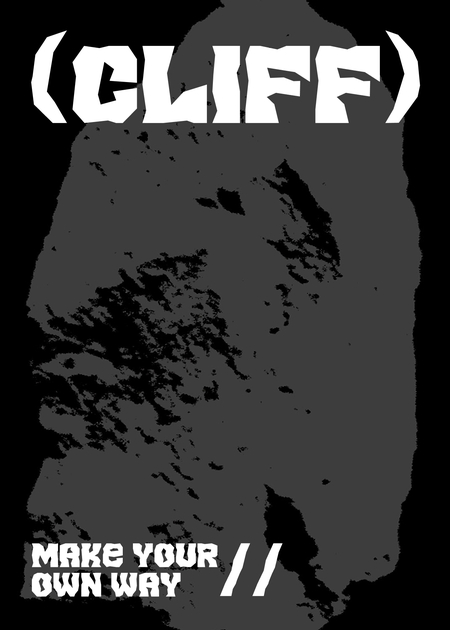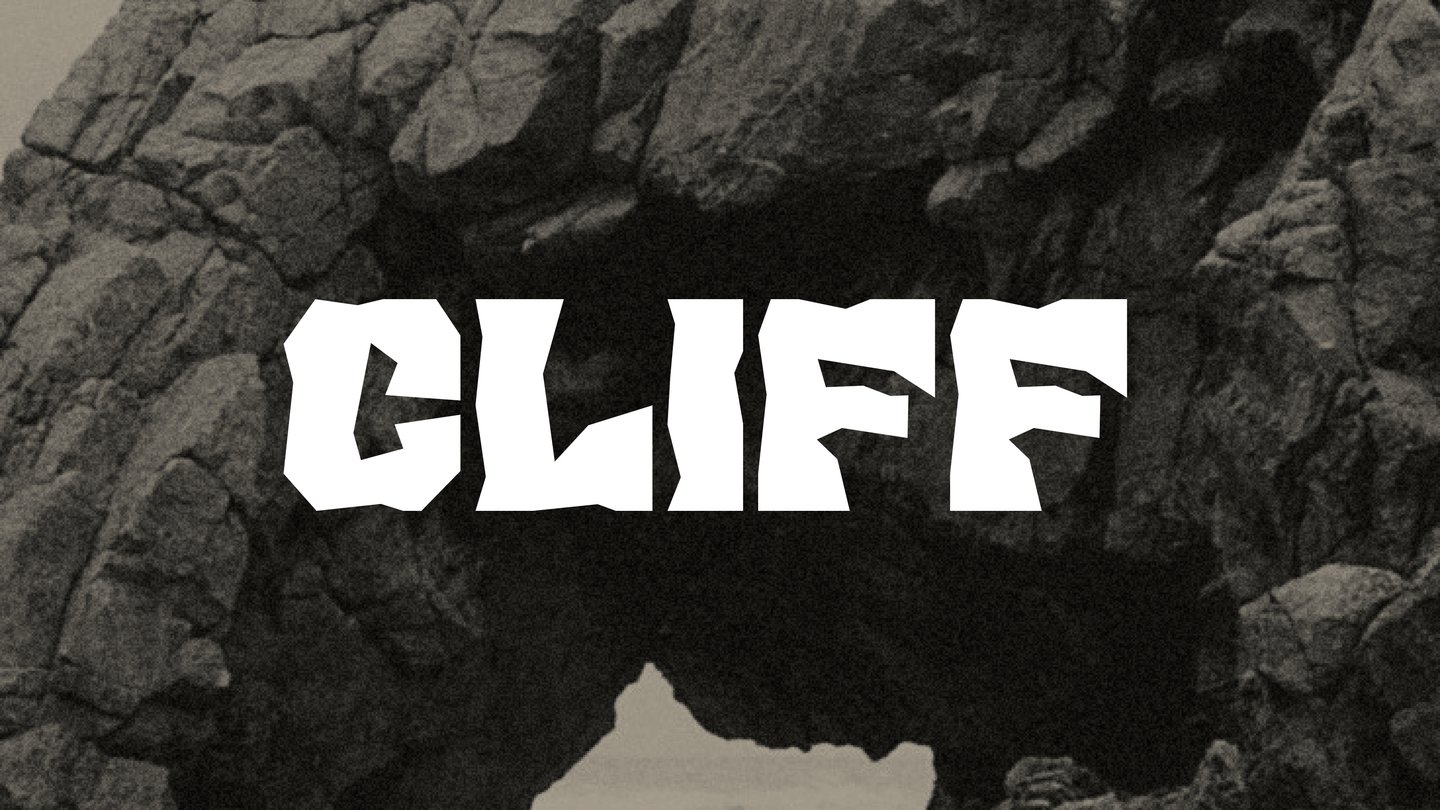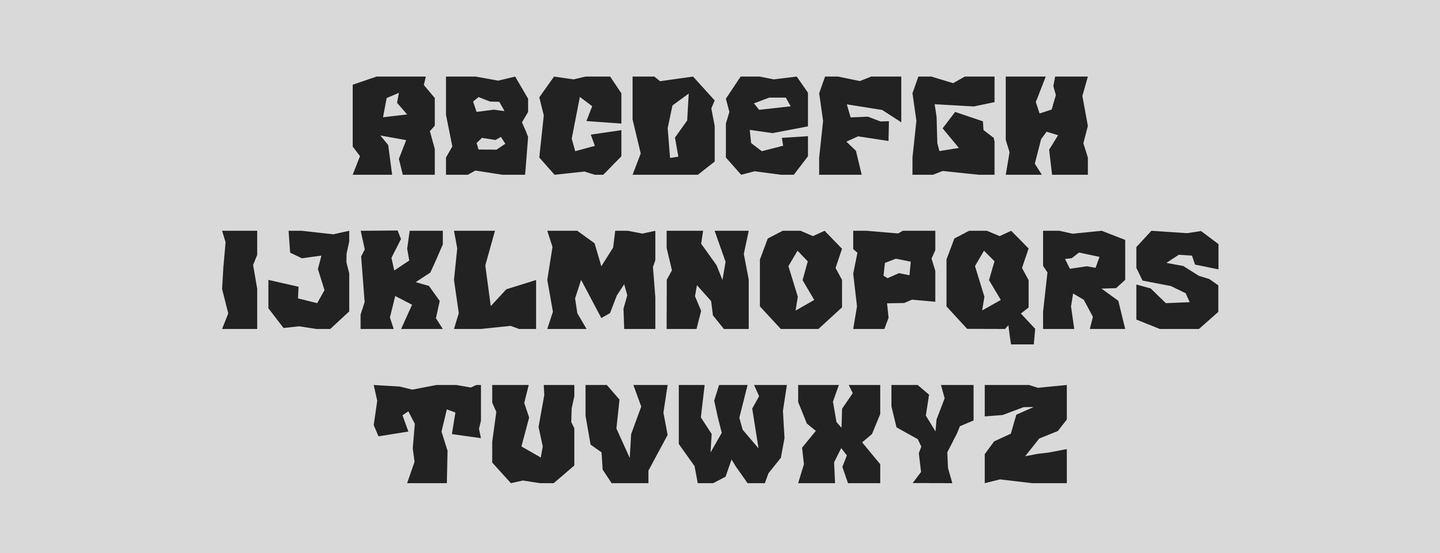
Cliff Font
Cliff Font — массивный, угловатый шрифт с рваной геометрией. Вдохновлён скалами, трещинами и природной силой. Он отлично передаёт настроение уличной культуры, андеграунда и антиглянцевых проектов. Cliff подходит для коротких, сильных сообщений, где важны характер и смелость.